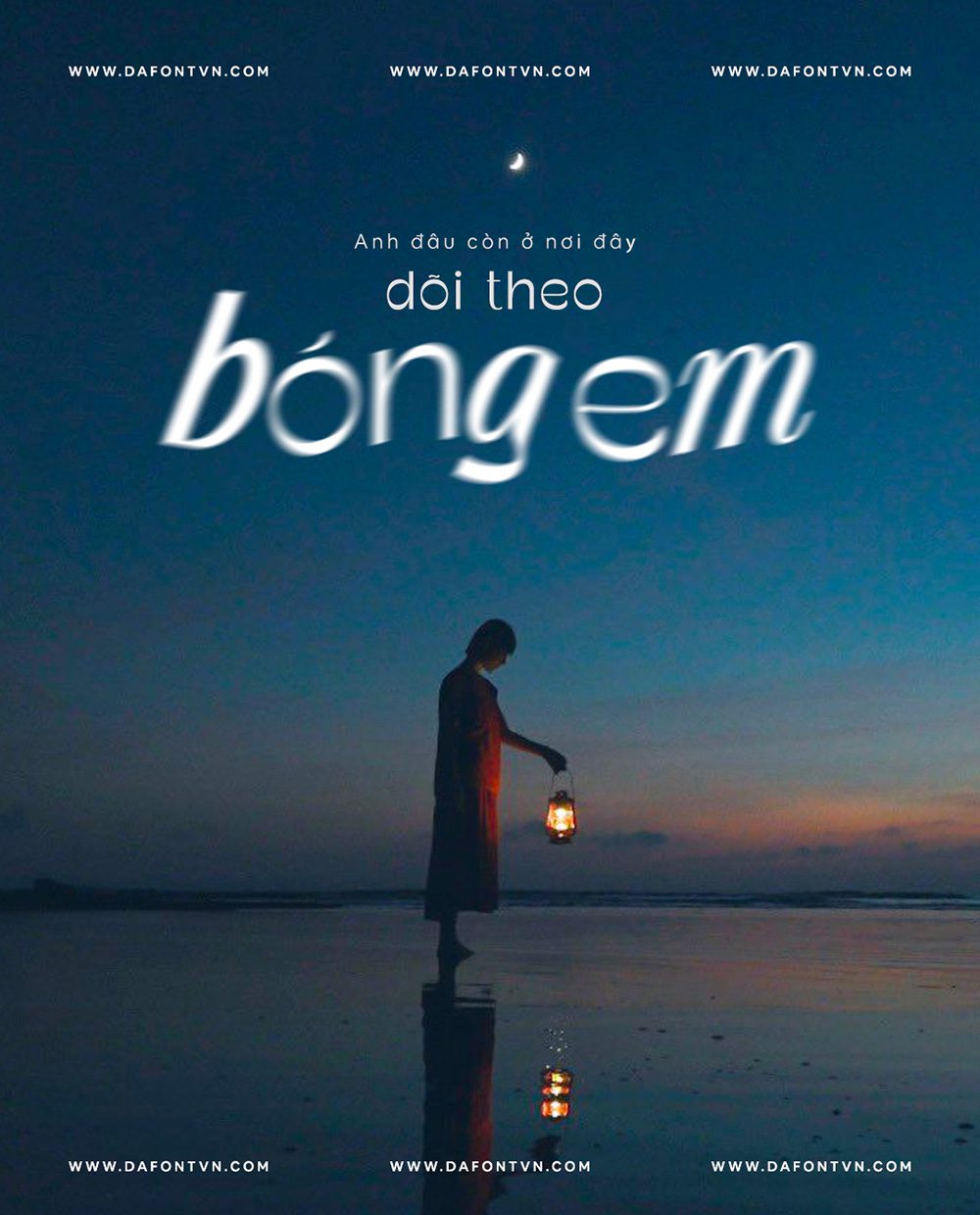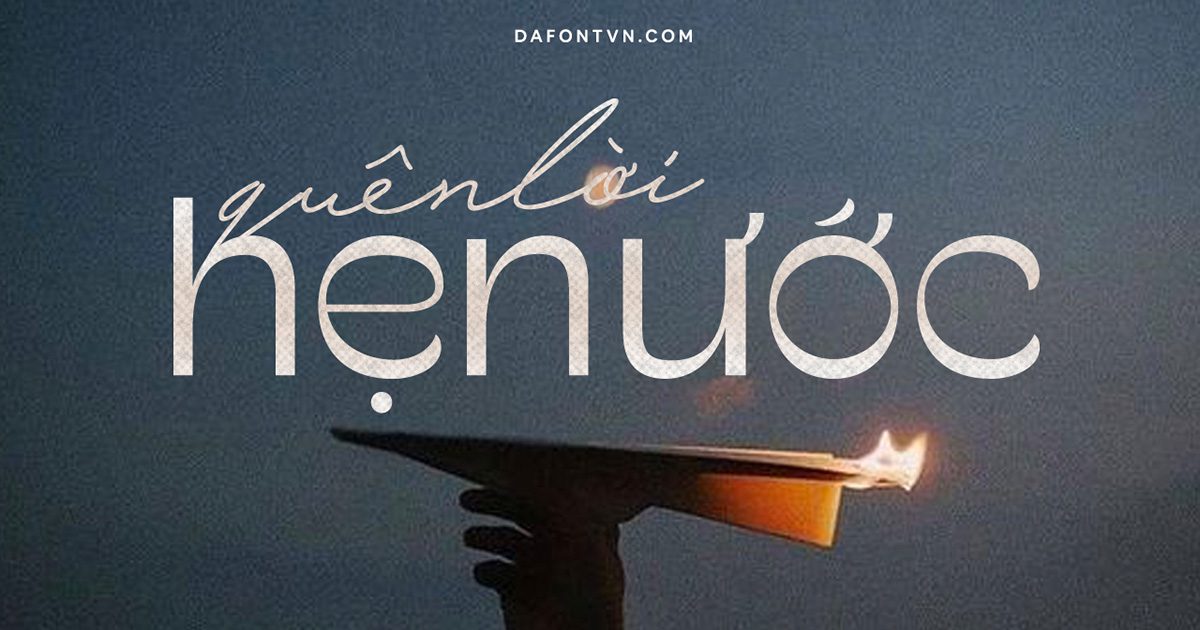
Trong thiết kế đồ họa, font chữ không chỉ là công cụ truyền tải nội dung mà còn là yếu tố quan trọng tạo nên cảm xúc, phong cách và dấu ấn riêng cho từng sản phẩm. Một thiết kế đẹp đôi khi không cần quá nhiều chi tiết phức tạp, chỉ cần lựa chọn đúng kiểu chữ là đã có thể tạo nên sự khác biệt rõ rệt. Trong số những phong cách được nhiều designer yêu thích hiện nay, các mẫu chữ thanh mảnh, mềm mại và tinh tế luôn có sức hút đặc biệt. Nổi bật trong nhóm này, TAN SPRING là một lựa chọn đáng chú ý dành cho những ai đang tìm kiếm Font Chữ Việt Hóa có vẻ đẹp nhẹ nhàng, hiện đại và giàu tính thẩm mỹ.
TAN SPRING mang đến cảm giác bay bổng, nữ tính và thanh lịch, rất phù hợp với các thiết kế cần sự tinh tế. Kiểu chữ này thường tạo ấn tượng bởi đường nét mảnh, dáng chữ mềm, khoảng cách cân đối và khả năng thể hiện tốt trong nhiều bố cục khác nhau. Khi được Việt hóa đầy đủ, font càng trở nên hữu ích hơn với designer Việt Nam, đặc biệt trong các dự án cần sử dụng tiếng Việt có dấu một cách chính xác và đẹp mắt.
TAN SPRING Là Gì?
TAN SPRING là một kiểu font mang phong cách nhẹ nhàng, thanh thoát và có tính trang trí cao. Font phù hợp với những thiết kế hướng đến cảm giác mềm mại, sang trọng, lãng mạn hoặc tối giản. Với đường nét tinh tế, TAN SPRING có thể giúp tiêu đề, tên thương hiệu, câu trích dẫn hoặc nội dung nổi bật trở nên cuốn hút hơn mà không cần quá nhiều hiệu ứng phụ trợ.
Điểm đặc biệt của font này nằm ở sự cân bằng giữa tính nghệ thuật và khả năng ứng dụng. Một số font trang trí thường rất đẹp khi nhìn riêng lẻ nhưng lại khó dùng trong thiết kế thực tế vì thiếu tính đọc rõ. TAN SPRING lại có ưu điểm là vẫn giữ được vẻ mềm mại trong khi đảm bảo độ nhận diện chữ tương đối tốt nếu được sử dụng đúng kích thước và bố cục.
Vì Sao Font Việt Hóa Quan Trọng?
Đối với designer làm việc với nội dung tiếng Việt, font Việt hóa là yếu tố cực kỳ quan trọng. Tiếng Việt có hệ thống dấu phong phú, nếu font không hỗ trợ đầy đủ ký tự có dấu, thiết kế rất dễ bị lỗi hiển thị, mất chữ hoặc làm bố cục trở nên thiếu chuyên nghiệp. Đây là lý do các bộ Font Chữ Việt Hóa luôn được nhiều người tìm kiếm và ưu tiên sử dụng.
Một font đẹp nhưng không hỗ trợ tiếng Việt đầy đủ sẽ gây khó khăn trong quá trình thiết kế, đặc biệt khi làm poster, banner, logo, menu, thiệp mời hoặc nhận diện thương hiệu. Ngược lại, font đã được Việt hóa tốt sẽ giúp designer thoải mái sáng tạo với nội dung tiếng Việt mà không phải chỉnh sửa thủ công từng ký tự.
Đặc Điểm Nổi Bật Của Font TAN SPRING
TAN SPRING không phải là kiểu font quá cầu kỳ hay nặng tính trình diễn. Sức hút của font nằm ở sự nhẹ nhàng, thanh mảnh và tinh tế trong từng đường nét. Đây là kiểu chữ phù hợp với các thiết kế cần sự mềm mại nhưng vẫn giữ được nét hiện đại.
Phong Cách Thanh Mảnh Và Tinh Tế
Đúng như tinh thần mà cái tên TAN SPRING gợi ra, font mang đến cảm giác tươi mới, nhẹ nhàng và có phần lãng mạn. Các đường nét mảnh giúp tổng thể thiết kế trở nên thoáng hơn, không gây cảm giác nặng nề. Khi đặt trên nền sáng, nền pastel hoặc nền ảnh có tông màu nhẹ, font có thể tạo ra hiệu ứng thị giác rất đẹp.
Phong cách thanh mảnh cũng giúp TAN SPRING phù hợp với các thiết kế cao cấp, đặc biệt là những sản phẩm liên quan đến thời trang, mỹ phẩm, làm đẹp, lifestyle, wedding, studio ảnh hoặc thương hiệu cá nhân.
Dễ Tạo Điểm Nhấn Cho Tiêu Đề
Một trong những ứng dụng tốt nhất của TAN SPRING là dùng cho tiêu đề chính. Với dáng chữ mềm và có tính thẩm mỹ cao, font giúp tiêu đề trở nên nổi bật mà không cần dùng quá nhiều hiệu ứng như đổ bóng, viền chữ hay texture phức tạp. Chỉ cần kết hợp cùng màu sắc phù hợp, khoảng cách chữ hợp lý và bố cục thoáng, bạn đã có thể tạo ra một thiết kế đẹp mắt.
Tuy nhiên, vì font có đường nét khá mảnh, designer nên cân nhắc khi sử dụng trên nền quá rối hoặc kích thước quá nhỏ. Để đảm bảo khả năng đọc, TAN SPRING nên được dùng cho heading, quote, logo text hoặc các dòng chữ ngắn thay vì đoạn văn dài.
Ứng Dụng Của TAN SPRING Trong Thiết Kế
Một bộ font đẹp sẽ phát huy giá trị tốt nhất khi được dùng đúng mục đích. Với phong cách thanh mảnh, TAN SPRING có thể ứng dụng trong nhiều dạng thiết kế khác nhau, từ ấn phẩm in ấn đến nội dung kỹ thuật số.
Thiết Kế Logo Và Nhận Diện Thương Hiệu
TAN SPRING rất phù hợp với các thương hiệu theo đuổi phong cách tinh tế, nữ tính hoặc tối giản. Ví dụ như studio chụp ảnh, shop thời trang, spa, thương hiệu mỹ phẩm, tiệm hoa, tiệm bánh, wedding planner hoặc các dự án cá nhân sáng tạo. Khi dùng font cho logo, bạn có thể kết hợp với biểu tượng đơn giản để tạo nên tổng thể thanh lịch và dễ ghi nhớ.
Thiết Kế Thiệp Mời, Poster Và Banner
Với các thiết kế thiệp cưới, thiệp mời sự kiện, poster nghệ thuật hoặc banner quảng bá sản phẩm, TAN SPRING có thể tạo cảm giác nhẹ nhàng và sang trọng. Font đặc biệt phù hợp với các layout có nhiều khoảng trắng, hình ảnh tinh giản và màu sắc dịu mắt. Khi kết hợp cùng các gam màu như kem, be, hồng nhạt, xanh olive, nâu nhạt hoặc trắng đen tối giản, thiết kế sẽ trở nên hài hòa hơn.
Thiết Kế Nội Dung Mạng Xã Hội
Các bài đăng trên Facebook, Instagram, Pinterest hoặc thumbnail video cũng có thể tận dụng TAN SPRING để tạo điểm nhấn. Đối với những nội dung về thời trang, làm đẹp, cảm hứng sống, trích dẫn nhẹ nhàng hoặc quảng bá sản phẩm handmade, font này giúp hình ảnh trở nên chuyên nghiệp và có cá tính hơn.
Nếu bạn đang tìm kiếm một mẫu Font Chữ Việt Hóa vừa đẹp mắt, vừa dễ ứng dụng, vừa mang lại cảm giác sang trọng và khác biệt, TAN SPRING chắc chắn là cái tên đáng để trải nghiệm. Sử dụng đúng cách, font này sẽ giúp thiết kế của bạn trở nên tinh tế, chuyên nghiệp và cuốn hút hơn trong mắt người xem.